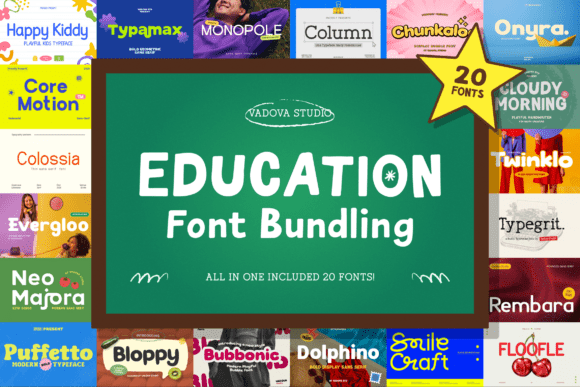
Education Bundle
Ulasan Lengkap Education Font Bundle – Font yang Membuat Belajar Jadi Lebih Ceria
Jika Anda sedang mencari tipografi yang dapat menambah semangat dan keceriaan pada semua materi edukasi, Education Font Bundle adalah pilihan yang tepat. Koleksi ini dirancang khusus untuk sekolah, anak‑anak, dan proyek kreatif berbasis pembelajaran, menawarkan playful dan friendly style yang mudah dikenali sekaligus tetap profesional.
Fitur Utama yang Membuatnya Menonjol
- 20 font eksklusif – kombinasi antara display berani, tulisan tangan yang bersahabat, dan huruf bergaya kartun.
- Desain ceria dan mudah dibaca – sempurna untuk poster kelas, buku anak, worksheet, dan media sosial.
Keunggulan untuk Pengguna Pendidikan
- Branding sekolah yang konsisten – warna dan bentuk huruf yang cerah membantu menciptakan identitas visual yang kuat.
- Materi pembelajaran yang menarik – font ini meningkatkan keterlibatan siswa pada buku kerja, poster, dan slide presentasi.
- Desain produk anak – cocok untuk sampul buku anak, stiker, dan perlengkapan menulis seperti notebook.
- Efisiensi produksi – satu paket mencakup semua gaya yang dibutuhkan, mengurangi waktu pencarian font lain.
Siapa yang Paling Membutuhkan?
- Guru dan tenaga pengajar yang ingin mempercantik materi kelas.
- Desainer grafis yang bekerja dengan brand edukasi atau tutoring.
- Pengelola sekolah dan lembaga kursus yang membutuhkan identitas visual yang ramah anak.
- Penulis dan ilustrator buku anak yang menginginkan tipografi yang “bercerita”.
- Pengusaha produk stationery dan perlengkapan belajar.
Dengan 20 font yang serbaguna, tampilan yang playful namun tetap profesional, serta lisensi komersial yang memadai, Education Font Bundle menjadi investasi yang sangat berharga bagi siapa saja yang bergerak di dunia pendidikan. Tingkatkan energi visual proyek Anda, buat materi belajar lebih engaging, dan biarkan tipografi ini menjadi “suara” ceria dalam setiap kelas atau produk edukasi.